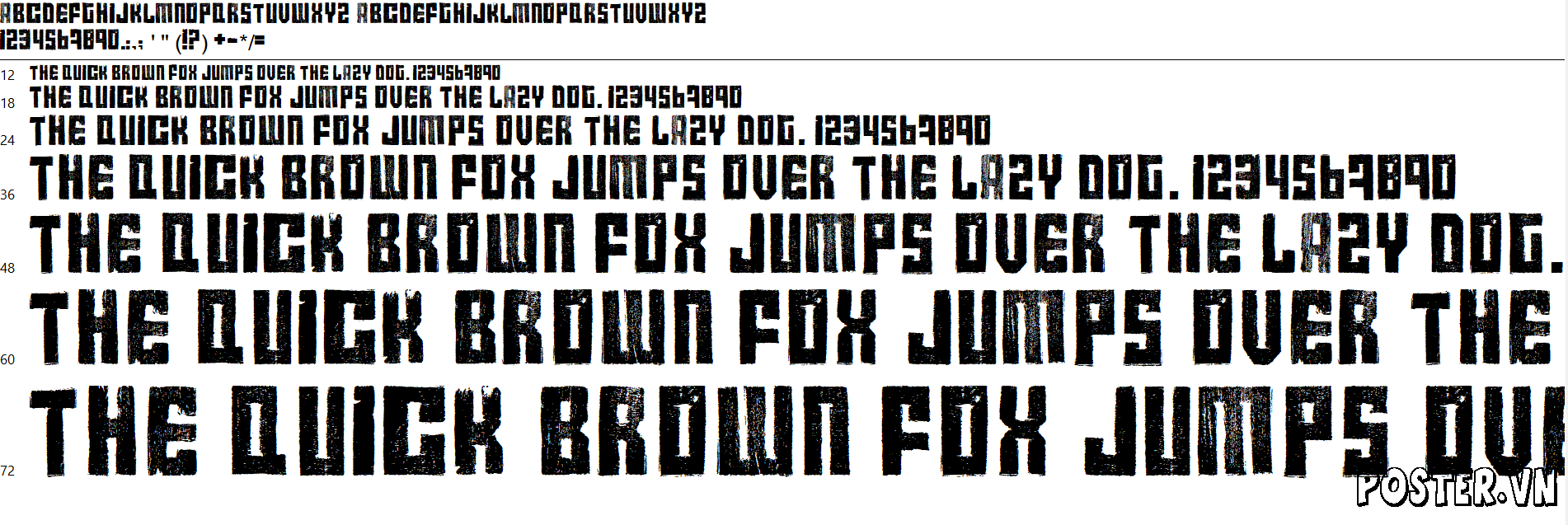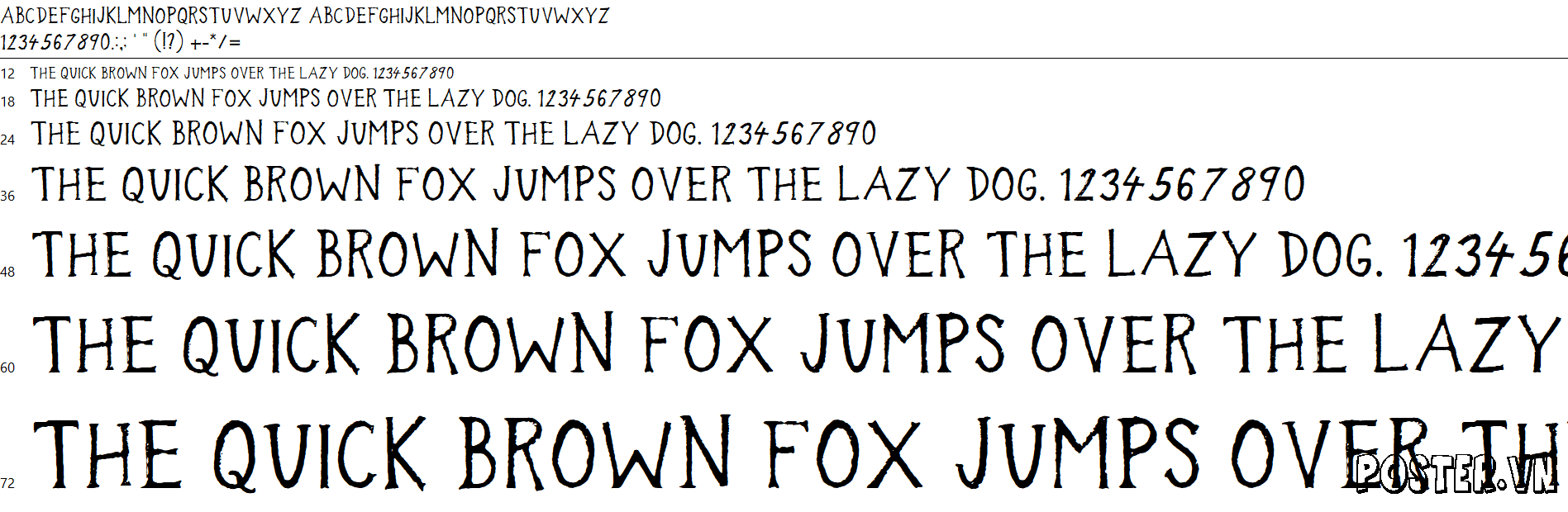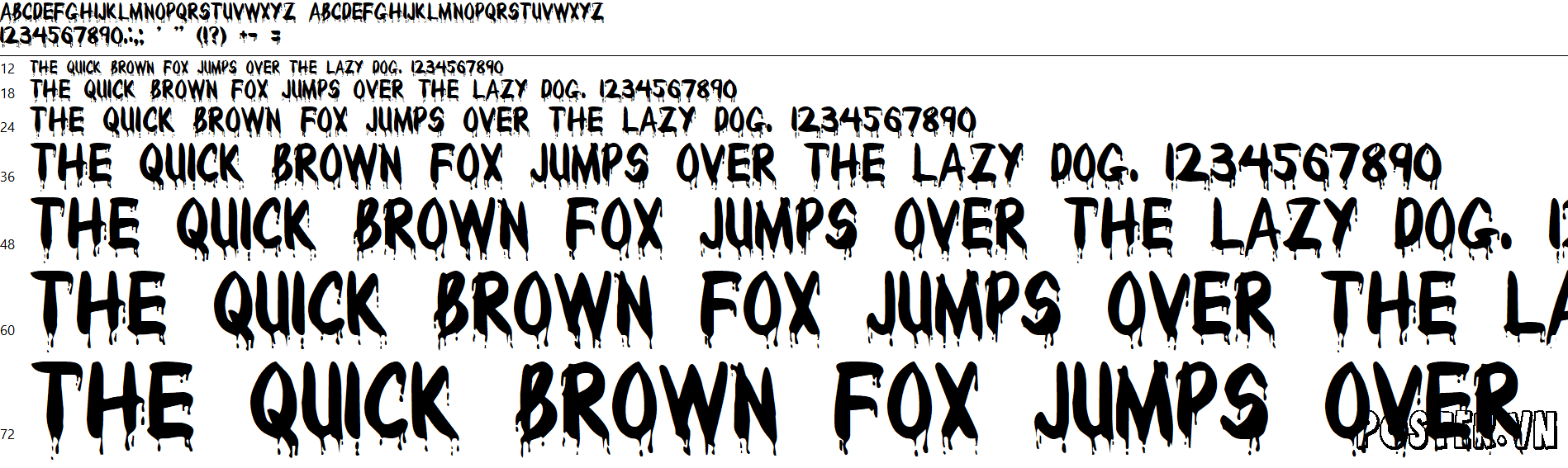
Bộ Sưu Tập 10 Font Chữ Kinh Dị Việt Hóa Độc Quyền: Gieo Rắc Nỗi Ám Ảnh Vào Mọi Thiết Kế Halloween
Bạn đã quá mệt mỏi với việc tìm được một font chữ kinh dị ưng ý nhưng lại hiển thị lỗi ô vuông (□□□) khi gõ tiếng Việt? Bạn tốn hàng giờ để “chế” dấu thủ công, làm thiết kế trở nên thiếu chuyên nghiệp? Poster.vn mang đến giải pháp tối thượng: bộ sưu tập “10 Font Chữ Kinh Dị” được tuyển chọn và Việt hóa hoàn chỉnh, được chế tác tỉ mỉ đến từng vết cào, giọt máu. Đây là bộ công cụ không thể thiếu cho mùa Halloween, giúp bạn thống trị mọi dự án từ poster phim, sự kiện cho đến các ấn phẩm social media.
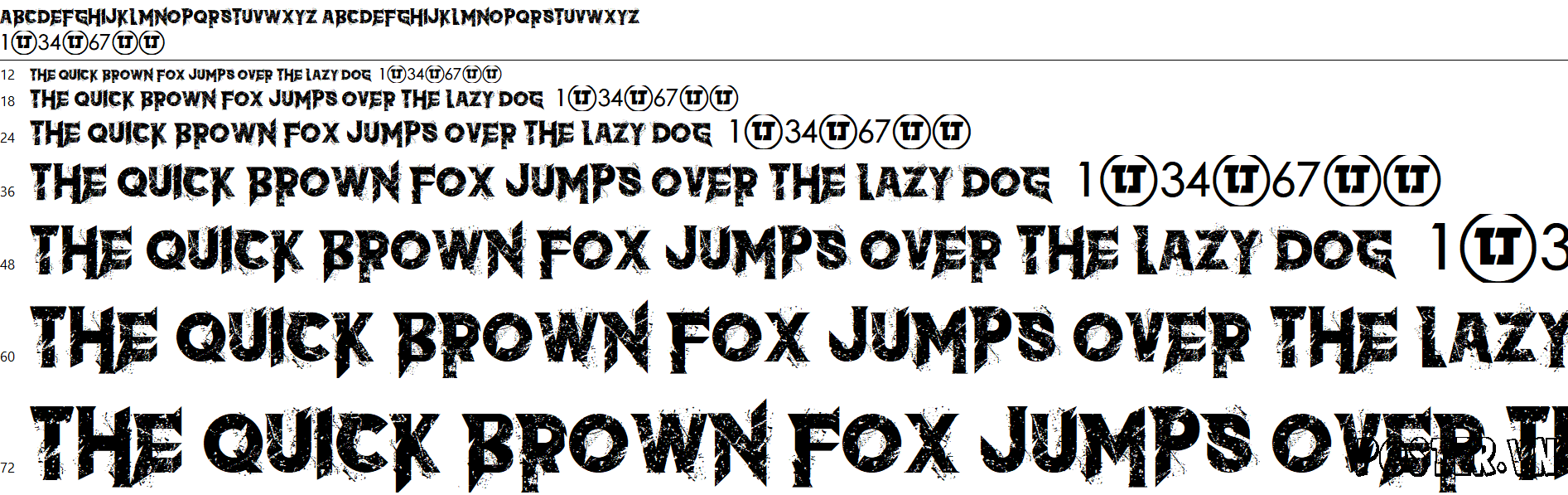
- Giải quyết triệt để vấn đề Việt Hóa: Đây là lý do cốt lõi và quan trọng nhất. Trong khi 99% font kinh dị miễn phí trên mạng không hỗ trợ tiếng Việt, bộ sưu tập của chúng tôi đã được đội ngũ chuyên gia Việt hóa một cách hoàn chỉnh. Mọi ký tự đặc biệt (ă, â, đ, ê, ô, ơ, ư) và tất cả các dấu thanh (huyền, sắc, hỏi, ngã, nặng) đều được thiết kế lại để hài hòa với phong cách ghê rợn của font gốc, đảm bảo tính thẩm mỹ và truyền tải trọn vẹn cảm xúc.
- Đảm bảo sự chuyên nghiệp và nhất quán tuyệt đối: Sử dụng một font chữ bị lỗi hoặc chắp vá khiến thiết kế của bạn trông rẻ tiền và thiếu chuyên nghiệp. Bộ sưu tập của chúng tôi đảm bảo mọi con chữ, từ tiêu đề poster phim, banner sự kiện Halloween cho đến các ấn phẩm quảng cáo, đều có một vẻ ngoài đồng nhất, chuyên nghiệp và đầy ám ảnh.
| Tiêu chí | Bộ 10 Font Chữ Kinh Dị tại Poster.vn | Font miễn phí từ các nguồn khác |
|---|---|---|
| Hỗ trợ Tiếng Việt | Việt hóa đầy đủ 100%. Tất cả ký tự và dấu thanh tiếng Việt được thiết kế tỉ mỉ, đồng bộ với phong cách ghê rợn của font gốc. Gõ là được, không lỗi, không hiển thị ô vuông. | Hầu như không hỗ trợ. Thường xuyên bị lỗi ký tự, thiếu dấu. Hiển thị ô vuông (□) là vấn đề phổ biến nhất, phá hỏng toàn bộ thiết kế. |
| Chất lượng & Tuyển chọn | Được tuyển chọn kỹ lưỡng từ hàng trăm font, đảm bảo 10 font đều đẹp, độc đáo và có tính ứng dụng cao. Chất lượng vector sắc nét. | Phải tự mình tìm kiếm, sàng lọc qua hàng trăm font kém chất lượng, lặp lại nhàm chán. Chất lượng không đồng đều, nhiều font bị lỗi kỹ thuật. |
Sự tin cậy không được xây dựng chỉ bằng lời nói, mà bằng cam kết và hành động, đặc biệt là trong các vấn đề kỹ thuật phức tạp như Việt hóa font chữ. Poster.vn cam kết trở thành một nền tảng vững chắc, nơi các nhà thiết kế Việt Nam có thể tự tin sáng tạo mà không bị giới hạn bởi các rào cản công nghệ. Chúng tôi tin rằng, khi bạn được trang bị những công cụ tốt nhất, được tạo ra bởi những người am hiểu sâu sắc về chuyên môn, bạn sẽ tạo ra những tác phẩm xuất sắc nhất.
• Kiểm tra Tính đầy đủ và Thẩm mỹ: Chúng tôi kiểm tra từng ký tự, từng dấu thanh để đảm bảo không có thiếu sót và hài hòa với thiết kế gốc.